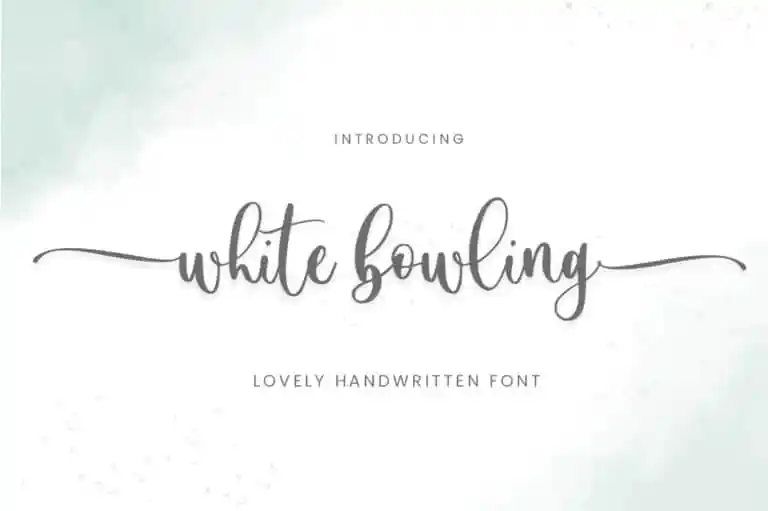
A White Bowling Calligraphy Font é uma elegante tipografia script moderna que oferece um toque clássico e delicado através de sua linha variável suave e arquitetônica. Este tipo digital foi criado pela Sronstudio e representa perfeitamente o conceito de fontes de escritura, ideal para aplicar em várias áreas, desde design gráfico até publicidade e embalagens de produtos. Perfeita para criar identidades visuais, convites e cartões-postais, a White Bowling Calligraphy Font também é uma ótima escolha para projetos digitais como posts nas redes sociais, água-marinhas em fotografias ou qualquer tipo de design especial ou publicidade. Ideal tanto para designers profissionais quanto para iniciantes na área da moda gráfica e design, essa fonte traz um toque singular a cada projeto onde é usada.